나눔 글꼴, 폰트 다운
네이버가 한글을 생각하는 마음을 담아 한 글자 한 글자 정성을 다해 언제 어디서 누구나 사용할 수 있는 '나눔글꼴을 만들었습니다.
글꼴종류 : 나눔고딕, 나눔고딕 D2coding, 나눔고딕에코, 나눔명조, 나눔명조에코, 나눔명조옛한글, 나눔바른고딕, 나눔바른고딕옛한글, 나눔바른펜 일반용, 나눔손글씨 붓, 나눔손글씨 펜, 나눔스퀘어, 나눔스퀘어 네오, 나눔스퀘어라운드
새로 나온 나눔스퀘어 네오 폰트는 나눔스퀘어 고유의 직선적인 형태를 계승한 글꼴로 친근한 미감과 안정적인 글줄이 특징이며, 다양한 환경에서 메시지를 주목도 있게 전달하기 좋은 글꼴입니다.
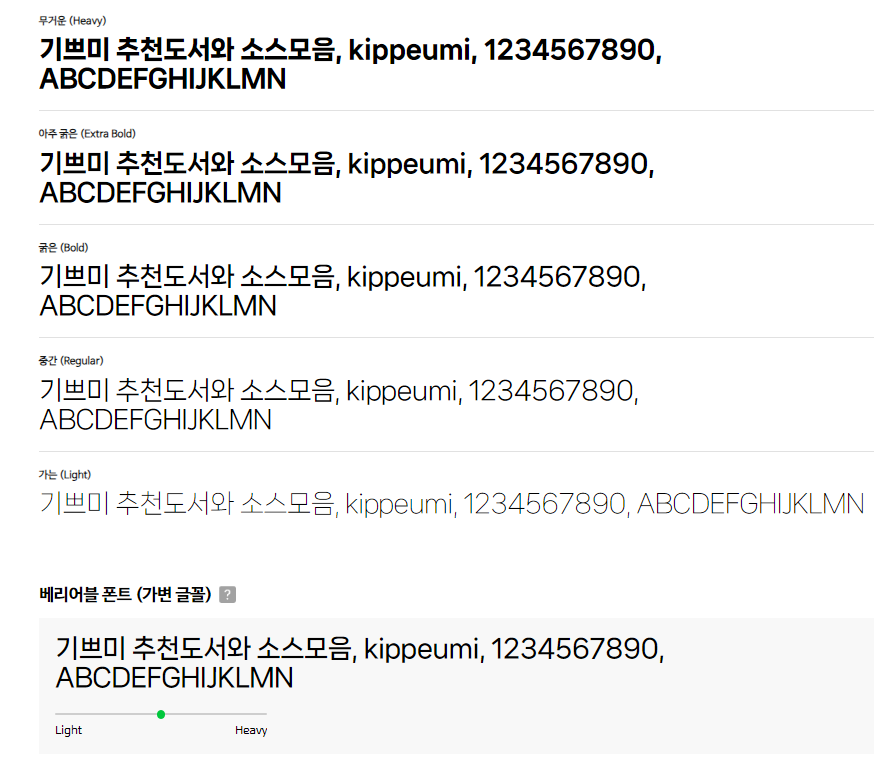
마루 부리 글꼴, 폰트 다운
'마루 부리'는 민부리(고딕) 위주의 환경에서 글꼴 선택의 폭을 넓히고, 한글꼴의 디지털 기틀을 만들기 위해 제작한 미래 세대를 위한 글꼴입니다.
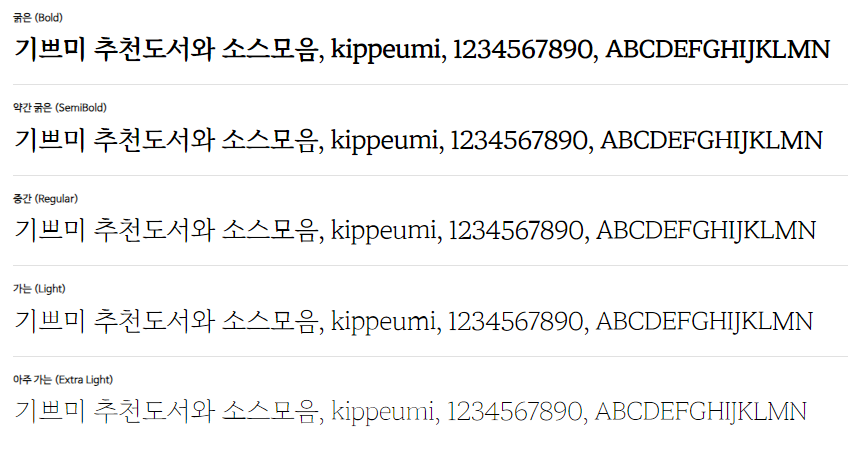
클로바 나눔손글씨, 폰트 다운
여러분의 손글씨와 클로바 AI기술이 만나 탄생한 새로운 '나눔손글씨' 글꼴입니다.
저마다의 이야기를 담은 109종의 글꼴을 만나보세요.